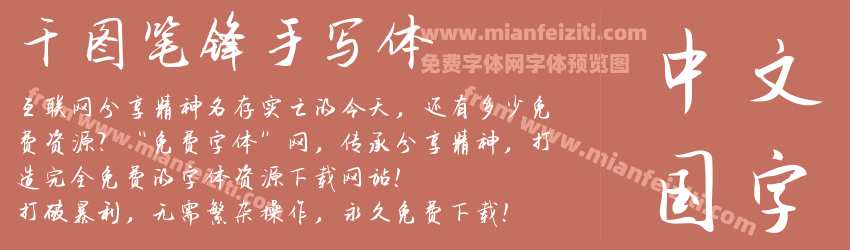
字体风格: 手写体
◇推荐场景:美食/地产广告/电商等
◇文字介绍:【千图笔锋手写体】定义为一款清新的创意手写字体。在字形笔画上改变了平直的笔画,用柔和的弧线将字体的柔美发挥的淋漓尽致,字形新颖独特,简洁有力,清新淡雅,文艺范十足。整体采用连笔写法,一气呵成,更显流畅。适用于海报 、影视综艺、文艺宣传等场景。
本款“千图笔锋手写体”是一款书写很新颖的字体,字体大方,适合各种设计作品使用!欢迎下载!